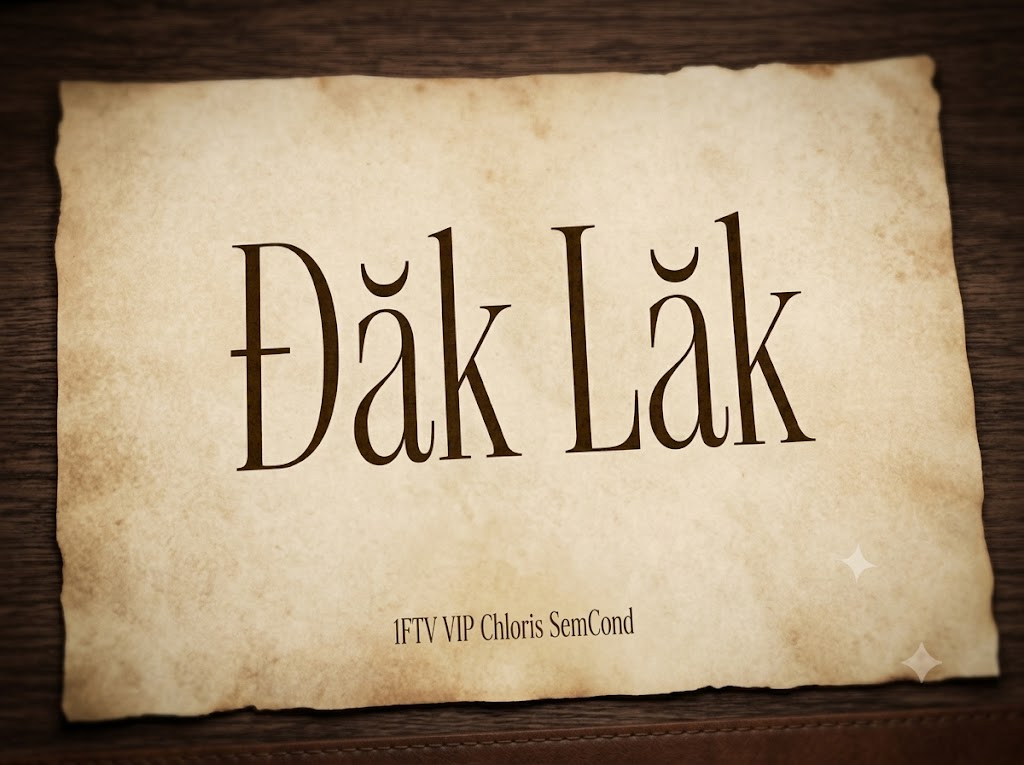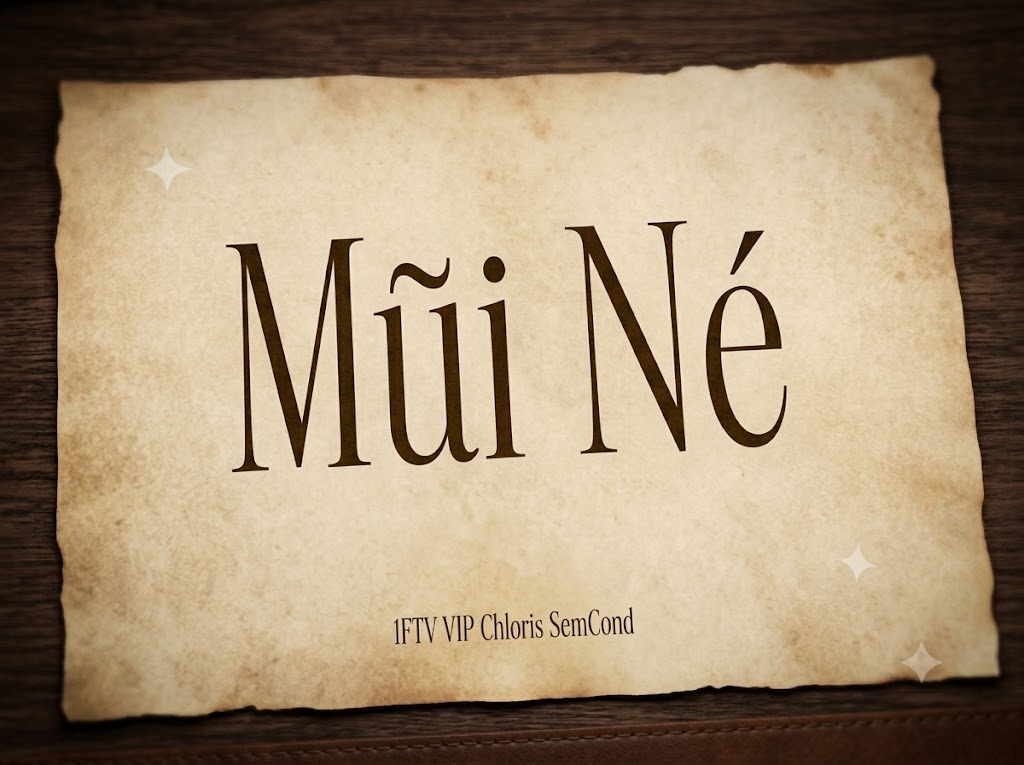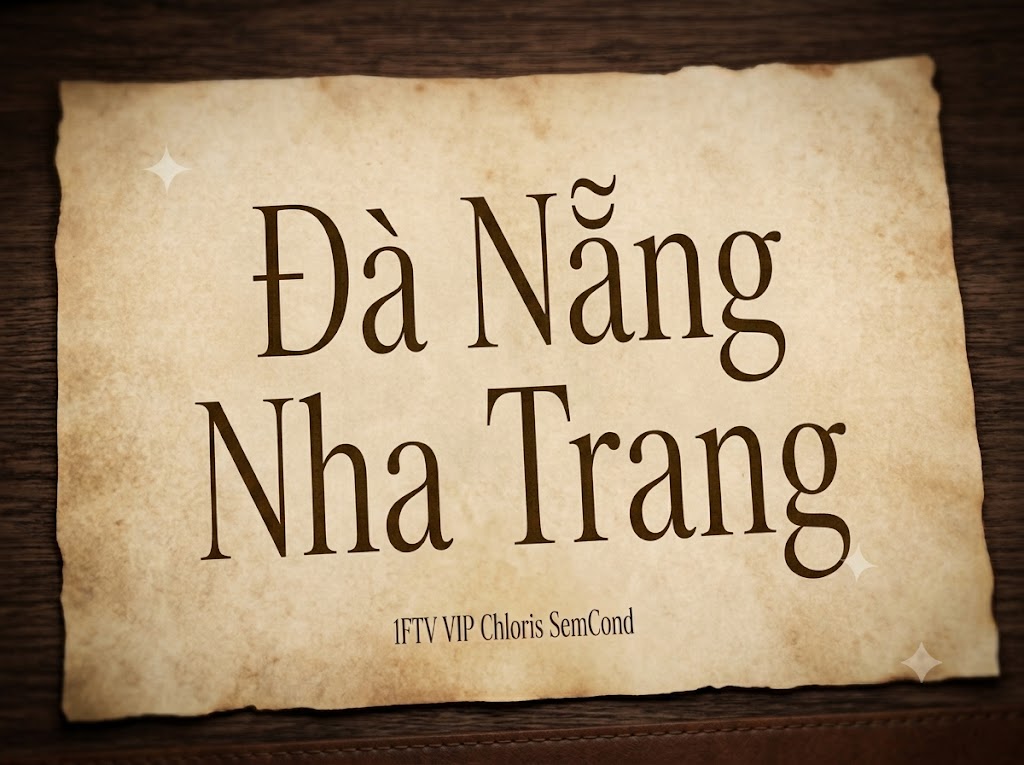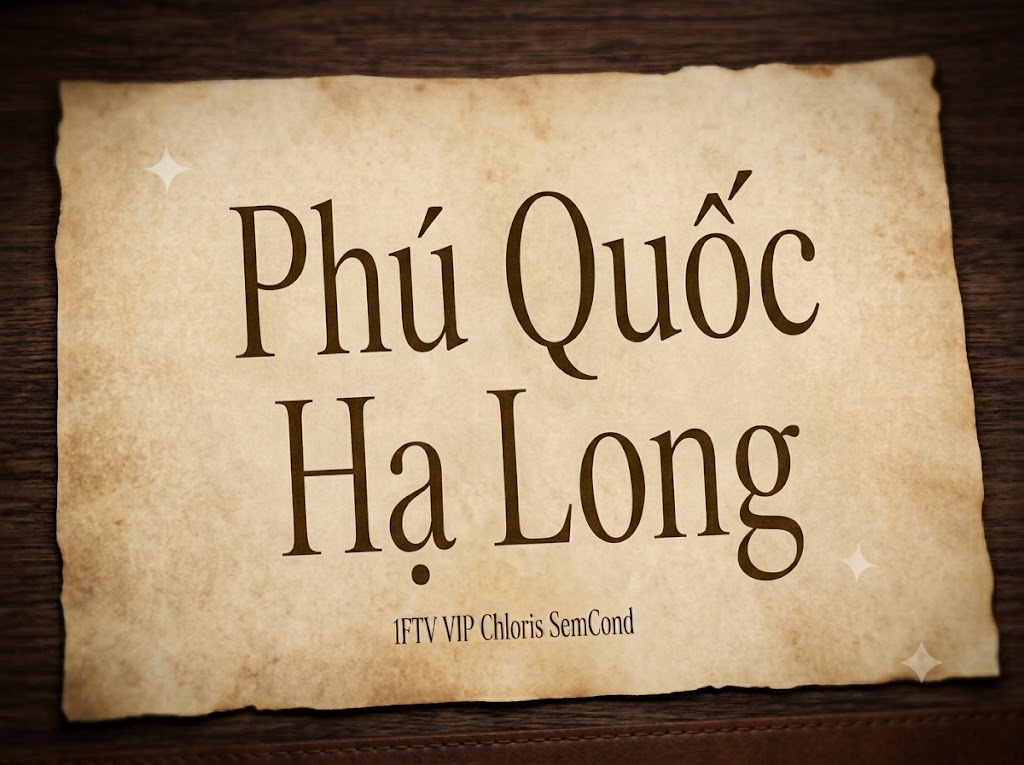
1FTV VIP Chloris SemCond
Trong thế giới thiết kế đồ họa cao cấp và định hình phong cách thương hiệu thời thượng, các phông chữ có chân (Serif) sở hữu độ tương phản nét cao luôn giữ một vị thế độc tôn. Chúng không chỉ đơn thuần là công cụ truyền tải thông tin, mà còn là tuyên ngôn về sự xa xỉ, tính nghệ thuật đương đại và tư duy duy mỹ đỉnh cao.
Khi không gian hiển thị đòi hỏi sự tinh gọn nhưng vẫn phải giữ trọn vẹn tinh thần quý phái của các tạp chí thời trang danh tiếng, một cấu trúc chữ semi-condensed (thuôn gọn vừa phải) chính là giải pháp typographic hoàn hảo.
Nếu bạn đang tìm kiếm một bộ chữ vừa mang nét kiêu kỳ, vừa tối ưu không gian hiển thị cho các dòng tiêu đề lớn hay bìa lookbook, thì font 1FTV VIP Chloris SemCond chính là kiệt tác dành cho bạn.
Giới thiệu về font 1FTV VIP Chloris SemCond
Font 1FTV VIP Chloris SemCond là một bộ chữ hiển thị có chân (serif display) được thiết kế theo trường phái tân cổ điển, hướng tới các tiêu chuẩn mỹ thuật tinh tế và phân khúc truyền thông luxury.
Tác phẩm này được hoàn thiện và tối ưu hóa hoàn chỉnh ở phiên bản Version 1.001, đem lại kết cấu đường nét mượt mà và sự đồng bộ tuyệt đối giữa các ký tự khi phối hợp tạo từ.
Sự đồng bộ kỹ thuật này giúp phông chữ hiển thị vô cùng sắc nét, mượt mà trên mọi phần mềm thiết kế và biên tập phim chuyên nghiệp, hoàn toàn không bị răng cưa hay vỡ cấu trúc nét khi bạn phóng to trên các bố cục khổ lớn.
Đặc điểm nổi bật của phong cách thiết kế Chloris SemCond
Sức hút mê hoặc của font 1FTV VIP Chloris SemCond đến từ sự kết hợp tài tình giữa cấu trúc hình khối thuôn gọn và vũ điệu nét thanh nét đậm cực kỳ sắc sảo:
Độ tương phản nét đỉnh cao: Sự chênh lệch rõ rệt giữa nét thanh siêu mảnh và nét đậm dày dặn mang lại chiều sâu thị giác đầy mê hoặc, gợi liên tưởng đến trang bìa của các tạp chí thời trang, nước hoa xa xỉ toàn cầu.
Phom dáng Semi-Condensed tối ưu: Dáng chữ được bóp gọn vừa phải theo chiều ngang giúp bạn dễ dàng chèn các dòng headline dài, các cụm từ giật tít vào không gian hẹp mà vẫn giữ được kích thước chữ lớn, không bị tràn viền hay phá vỡ bố cục chung.
Hỗ trợ hệ ký tự hoa – thường đồng bộ: Khác với nhiều dòng font luxury chỉ hỗ trợ chữ in hoa, Chloris SemCond tích hợp trọn vẹn cả hệ thống chữ cái thường và chữ viết hoa đồng bộ, tạo nên một nhịp điệu đọc vô cùng thoáng đãng, tự nhiên và uyển chuyển.
Để phông chữ vận hành hoàn hảo trên mọi hệ điều hành từ Windows đến macOS, phiên bản font 1FTV VIP Chloris SemCond đã trải qua quy trình xử lý thông số kỹ thuật nội tại vô cùng nghiêm ngặt:
Hệ thống khoảng cách chữ (kerning) và độ giãn dòng (tracking) đã được căn chỉnh chuẩn xác đến từng pixel, giúp các nét chữ mảnh khi đứng cạnh nhau luôn giữ được khoảng trống thẩm mỹ lý tưởng, tạo cảm giác vô cùng thông thoáng và dễ chịu cho mắt người đọc.
Tích hợp đầy đủ bộ chữ cái hoa – thường, dãy chữ số từ 0-9 dáng đứng thanh lịch cùng hệ thống các ký tự đặc biệt, dấu câu thông dụng (
Bản Việt hóa chuẩn chỉnh giúp các nhà sáng tạo nội dung hoàn toàn yên tâm thiết kế các văn bản tiếng Việt có dấu mà không lo gặp phải tình trạng nhảy font hay lỗi hiển thị ký tự khó chịu.
Hình ảnh demo thực tế của font 1FTV VIP Chloris SemCond
Để giúp bạn dễ dàng hình dung khả năng co giãn và hiển thị linh hoạt của phông chữ này trên các kích thước khác nhau, hãy cùng xem qua bảng mô phỏng thực tế
Kích thước nhỏ (12pt – 24pt): Dù sở hữu các đường nét thanh đậm có độ tương phản lớn, cấu trúc chữ đứng và các dấu tiếng Việt vẫn hiển thị rất rõ ràng, ngay ngắn, tạo trải nghiệm đọc mượt mà trên các giao diện hiển thị di động.
Kích thước lớn (36pt – 72pt): Đây là đất diễn hoàn hảo nhất để font chữ phô diễn toàn bộ sự kiêu sa, quý phái của các đường nét vát nhọn và nét thanh siêu mảnh, tạo hiệu ứng thị giác đỉnh cao chiếm trọn sự chú ý cho các dòng headline chính.
Ứng dụng của font Chloris SemCond trong thiết kế đồ họa và làm video
Sở hữu nét cá tính sang trọng, quý phái và cấu trúc hình khối semi-condensed tinh tế, font 1FTV VIP Chloris SemCond mở ra không gian ứng dụng vô cùng rộng lớn cho các dự án truyền thông hiện đại:
Làm tiêu đề cho video ngắn (TikTok, Reels, Shorts): Kiểu chữ serif dáng thuôn gọn này hiển thị vô cùng ấn tượng trên các khung hình đứng tỷ lệ 9:16 của thiết bị di động. Độ mảnh mai và ráo hoảnh của chữ giúp dòng giật tít hiển thị một cách tự nhiên, cuốn hút người xem lướt feed dừng lại ngay lập tức mà không che mất chủ thể chính của video.
Thiết kế bìa tạp chí, Lookbook và Poster nghệ thuật: Hoàn hảo cho các ấn phẩm truyền thông thuộc lĩnh vực thời trang xa xỉ, mỹ phẩm cao cấp, trang sức, kiến trúc đương đại hoặc các triển lãm nghệ thuật sang trọng.
Ảnh thu nhỏ mạng xã hội (Thumbnail) phong cách sang trọng: Đây là vũ khí tuyệt vời để tạo nên những chiếc thumbnail YouTube, TikTok mang tính nghệ thuật, cao cấp cho các vlog phong cách sống, làm đẹp, e-commerce thời trang nhằm nâng cao tỷ lệ nhấp chuột nhờ giao diện chuyên nghiệp.